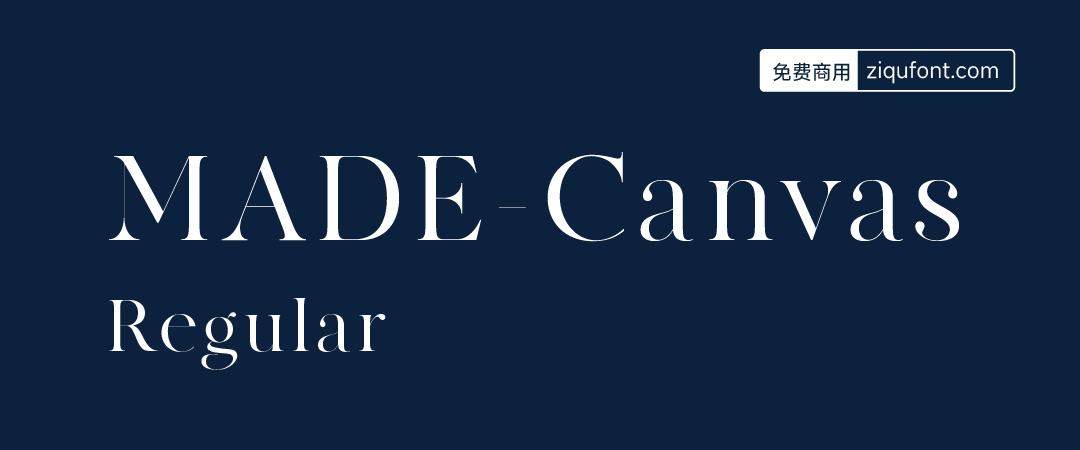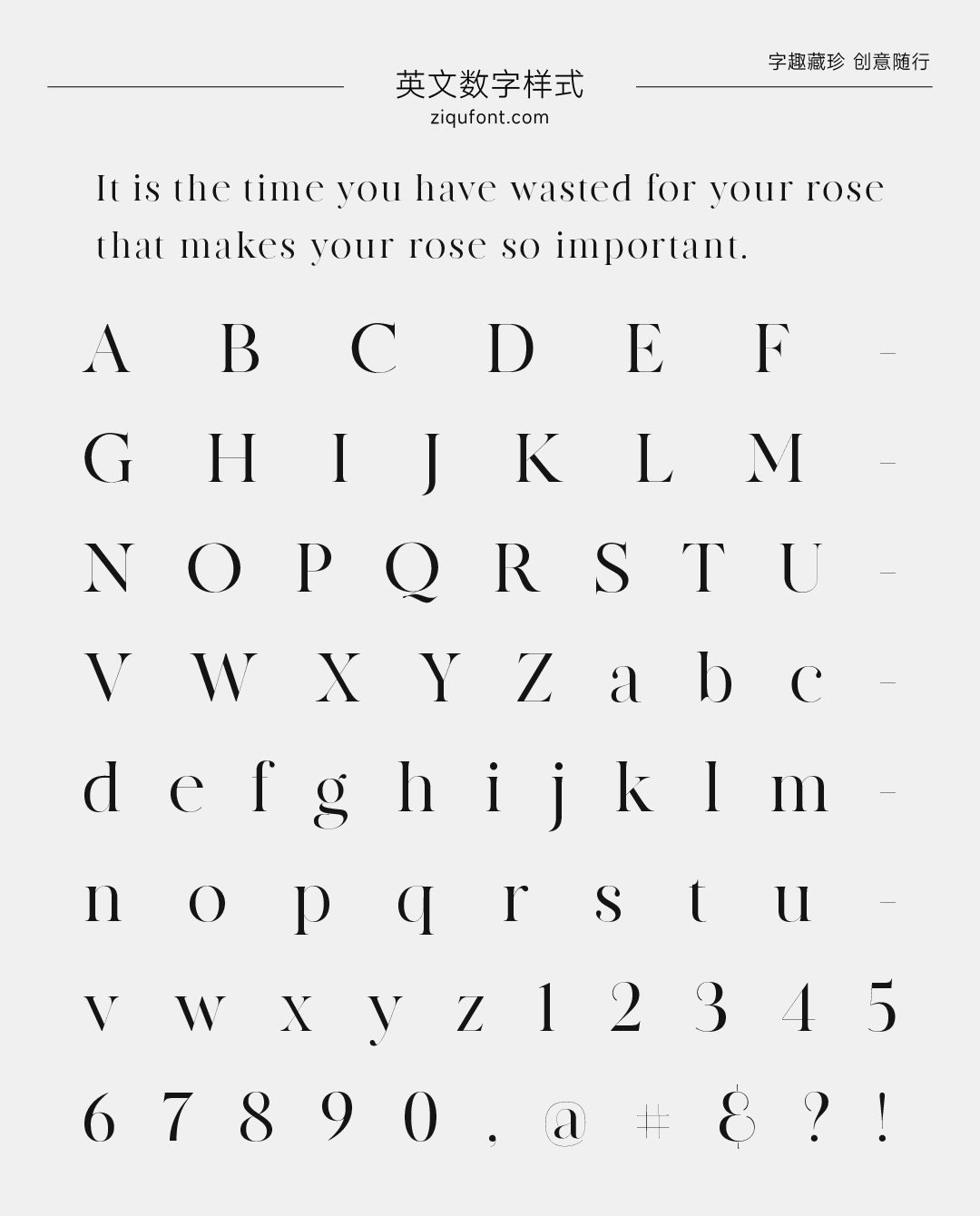
MADE-Canvas-Regular
MADE – Canvas – Regular 属于高对比度衬线字体,具有现代风格的 “Didoni” 特征。其笔画粗细对比强烈,细线条部分极为纤细,给人一种精致、优雅的感觉,同时粗线条部分又足够粗壮,增强了字体的视觉冲击力,整体呈现出简洁而有力的视觉效果。
MADE-Canvas-Regular